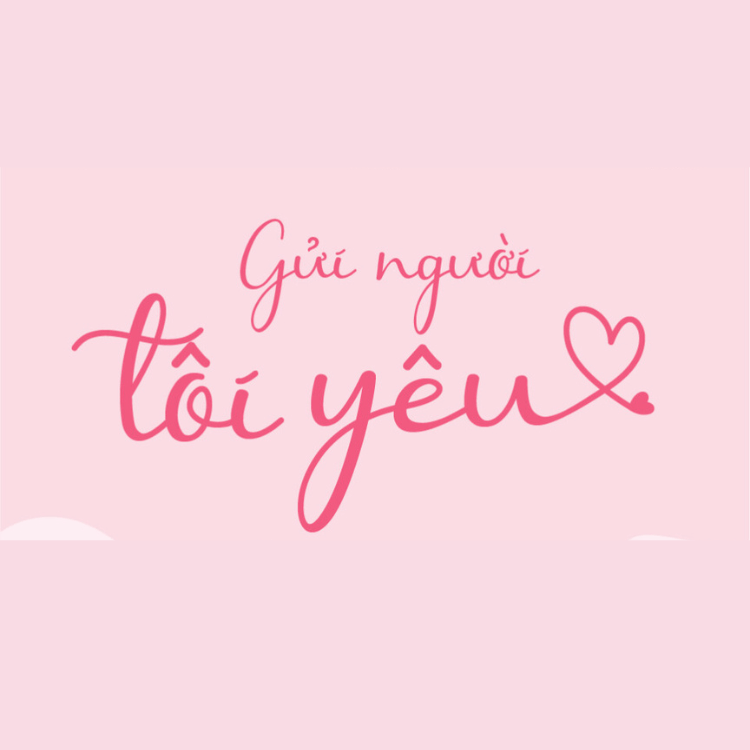
Giới thiệu về Font Việt hóa VIP Selly Calligraphy , Font cho valentine
Trong thế giới thiết kế đồ họa, việc lựa chọn một bộ Font Miễn Phí chất lượng luôn là ưu tiên hàng đầu của các bạn học sinh và giáo viên. Đặc biệt, khi mùa lễ hội tình yêu đang đến gần, nhu cầu tìm kiếm Font Việt hóa VIP Selly Calligraphy , Font cho valentine ngày càng tăng cao. Đây là bộ font mang phong cách thư pháp hiện đại, sở hữu những đường nét uyển chuyển, mềm mại và cực kỳ sang trọng. Việc sử dụng Selly Calligraphy giúp các bạn dễ dàng tạo ra những tấm thiệp chúc mừng, các bài thuyết trình hay tài liệu học tập có tính thẩm mỹ cao, truyền tải trọn vẹn thông điệp yêu thương đến người nhận.
Ưu điểm nổi bật của Font Việt hóa VIP Selly Calligraphy
Bộ font này được cộng đồng thiết kế đánh giá cao nhờ khả năng tương thích tốt với các phần mềm phổ biến như Photoshop, Canva hay Microsoft Word. Điểm đặc biệt của Font Việt hóa VIP Selly Calligraphy , Font cho valentine chính là hệ thống ký tự thay thế phong phú, cho phép người dùng sáng tạo những kiểu chữ độc bản. Các nét thanh, nét đậm được tinh chỉnh kỹ lưỡng, giúp văn bản tiếng Việt không bị lỗi dấu, đảm bảo sự đồng nhất và chuyên nghiệp cho mọi bản thiết kế nghệ thuật.
Cách ứng dụng Font cho valentine hiệu quả trong học tập
Đối với các hoạt động tại nhà trường, giáo viên có thể dùng bộ font này để trang trí bảng tin hoặc làm tiêu đề cho các báo tường chủ đề tình bạn. Học sinh có thể tận dụng những đường nét bay bổng để làm mới bìa sổ tay hoặc thiết kế quà tặng handmade. Sự kết hợp giữa màu sắc nhẹ nhàng và kiểu chữ thư pháp sẽ làm nổi bật tinh thần của ngày Valentine, tạo nên sự gần gũi và ấm áp trong môi trường giáo dục.